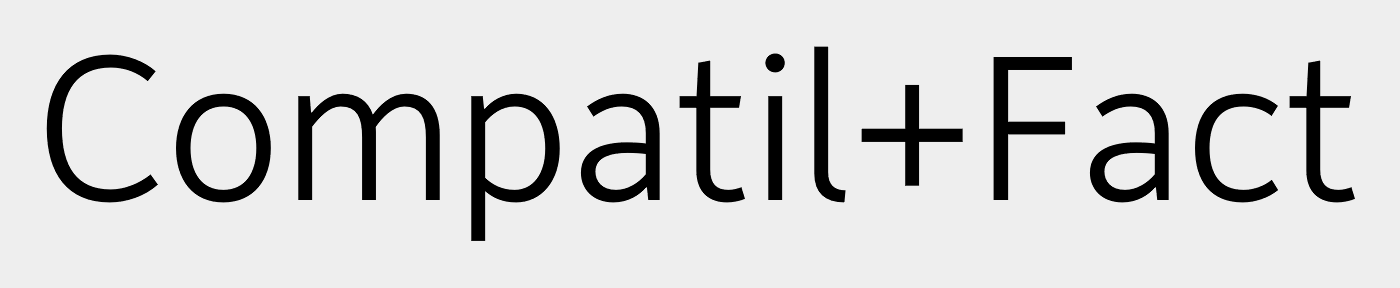
Alternativen für Compatil Fact?
Die COMPATIL FACT ist für geschäftliche Dokumente (Berichte, Präsentationen etc.) in jeder
Schriftgröße bestechend prägnant u. neutral mit konstanter Laufweite- nur leider sehr teuer.
Hättet Ihr evtl. erstklassige Alternativ-Empfehlungen?
Gibt es evtl. noch weitere Vorschläge?
Ich bin mal wieder, ohne es zu wollen, bei der Compatil Fact gelandet. Bei der letzten Anwendung hat mich gestört, dass es nur zwei Dicken gibt: Regular und Bold. Für eine Firma mit Werbeanwendungen kam ich da immer in die Bredouille.
Trotzdem liebe ich die Eigenständigkeit der Schrift, die trotz dessen ein wunderbar ruhiges Schriftbild hat! Gibt es eine Alternative, die dies auch vereint?
Die Corporate S ist mir doch ein wenig zu uneigenständig und sie hat ein doch unruhigeres/gedrungeneres Schriftbild.
Danke, ja, die hatte ich auch schon in der engeren Wahl, aber das Schriftbild ist mir zu unruhig.
Von den Schriftschnitten natürlich super …
… aber das Schriftbild ist mir zu unruhig.
Das habe ich auch noch nicht gehört. Ist Luc(as) de Groot nicht bekannt für seine besonders gut ausgeglichenen Schriftentwürfe?
Und was ist mit FF Kievit? Oder willst Du es einfach formal nur ruhiger – also eher in Richtung Frutiger?
Das habe ich auch noch nicht gehört. Ist Luc(as) de Groot nicht bekannt für seine besonders gut ausgeglichenen Schriftentwürfe?
Das weiß ich nicht, aber ich würde schätzen, dass alle bekannten Schriftenentwerfer gut ausgeglichene Schriften erstellen.
Wahrscheinlich ist die Thesis Sans doch noch eigenständiger, mehr auf Mengentext und kleinere Schriftgrade hin entwickelt, so dass sie etwas schmaler läuft und insgesamt weniger ruhig wirkt wie die Compatil. Wie auch immer, wenn man sie nebeneinander legt, sieht man es eindeutig.
Aber, die Kievit, danke für den Tipp. Die sieht sehr gut aus!
Mein Favorit ist die Source Sans Pro, danach die Kievit.
Und ich habe noch die Riga entdeckt.
Trotzdem fand ich es schwer anhand von unterschiedlichen PDFs-Schriftproben die Schriften zu vergleichen (bei Fontshop sind die Schriftmuster-PDFs aber größtemteils gleich. Leider aber auch nur 5 Zeilen Fließtext …). Dass es nicht so etwas gibt, dass man sich ein PDF mit eigenem Schriftmuster zusammenstellen und herunterladen kann … Das würde die Auswahl erleichern. Oder einen (aufs wesentliche reduzierten) Schnitt für 5€ …